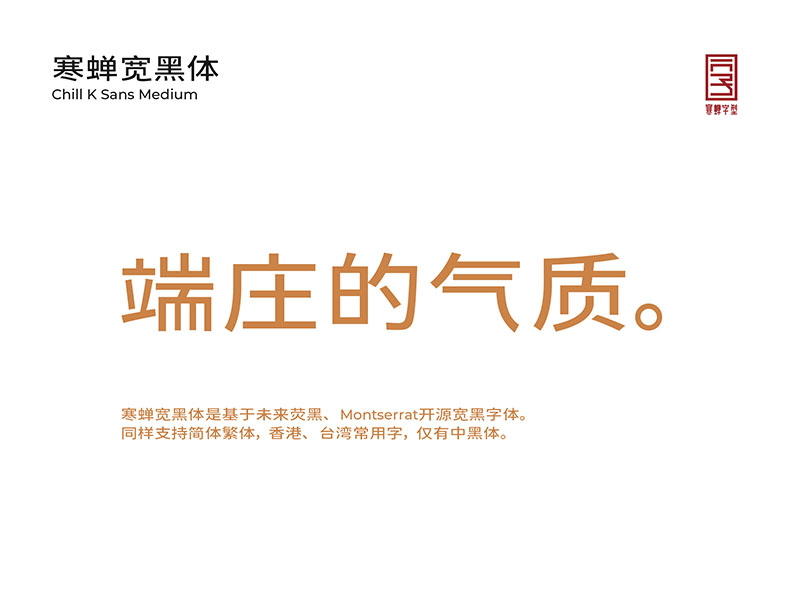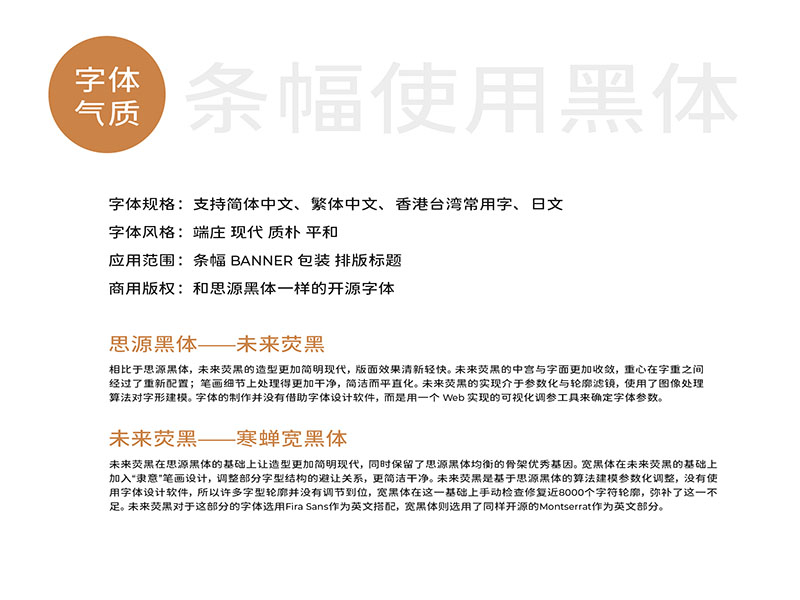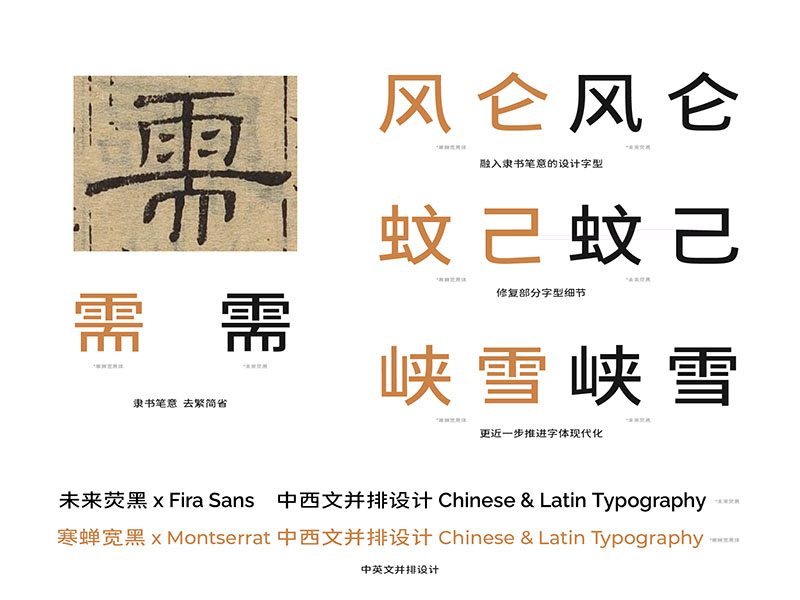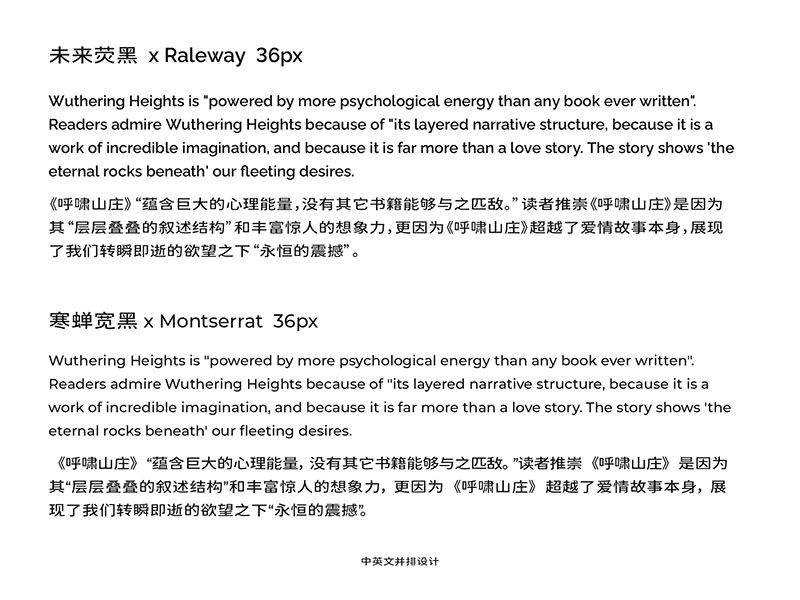
寒蟬寬黑體在未來熒黑的基礎上加入“隸意”筆畫設計,調整部分字型結構的避讓關係,更簡潔乾淨。重新選用了同樣開源的Montserrat作為英文部分。
條幅使用字體
字體規格:支持簡體中文、繁體中文、香港臺灣常用字、日文
字體風格:端莊現代質樸平和
應用範圍:條幅BANNER 包裝排版標題
思源黑體——未來熒黑
相比于思源黑體,未來熒黑的造型更加簡明現代,版面效果清新輕快。未來熒黑的中宮與字面更加收斂,重心在字重之間經過了重新配置;筆畫細節上處理得更加乾淨,簡潔而平直化。未來熒黑的實現介於參數化與輪廓濾鏡,使用了圖像處理算法對字形建模。字體的製作並沒有藉助字體設計軟件,而是用一個Web 實現的可視化調參工具來確定字體參數。
未來熒黑——寒蟬寬黑
未來熒黑在思源黑體的基礎上讓造型更加簡明現代,同時保留了思源黑體均衡的骨架優秀基因。寬黑體在未來熒黑的基礎上加入“隸意”筆畫設計,調整部分字型結構的避讓關係,更簡潔乾淨。未來熒黑是基於思源黑體的算法建模參數化調整,沒有使用字體設計軟件,所以許多字型輪廓並沒有調節到位,寬黑體在這一基礎上手動檢查修復近8000個字符輪廓,彌補了這一不足。未來熒黑對於這部分的字體選用Fira Sans作為英文搭配,寬黑體則選用了同樣開源的Montserrat作為英文部分。